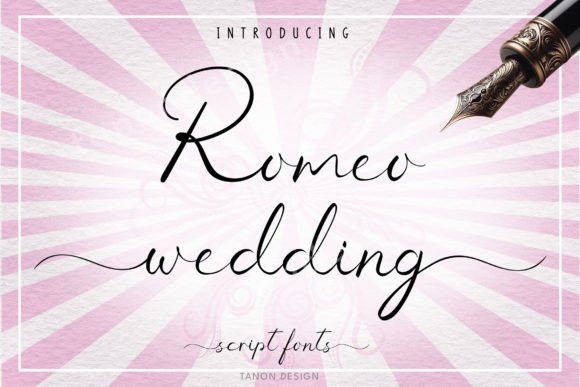
Romeo Wedding
適切なデザイン要素を見つけるのは難しい場合がありますが、Romeo Weddingは作品を即座に引き立てる優れたコレクションを提供します。
POD(オンデマンド印刷)製品、結婚式の招待状、またはソーシャルメディアのグラフィックを作成している場合でも、Romeo Weddingは理想的です。